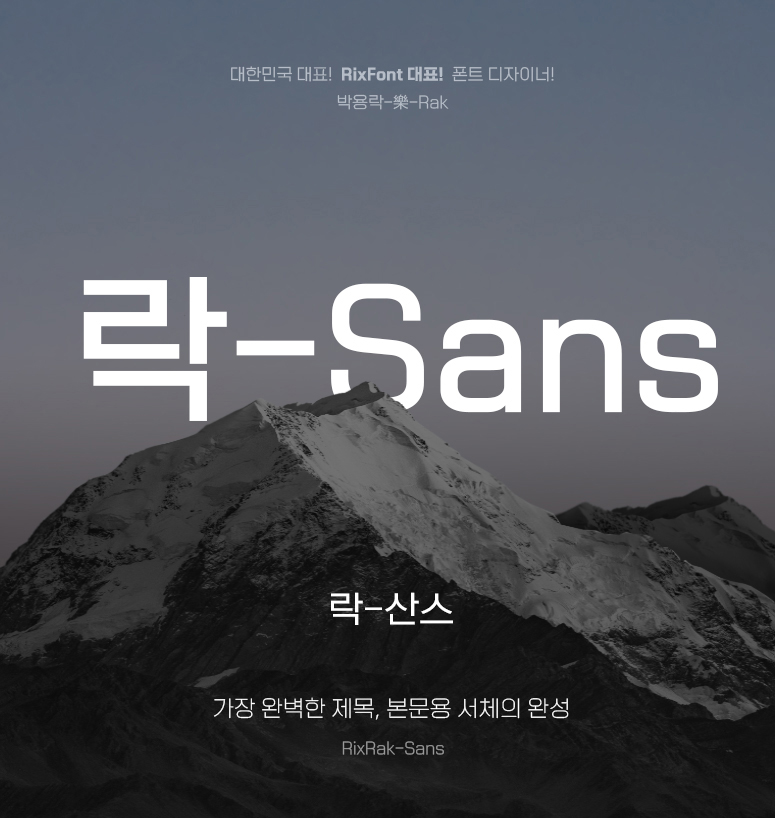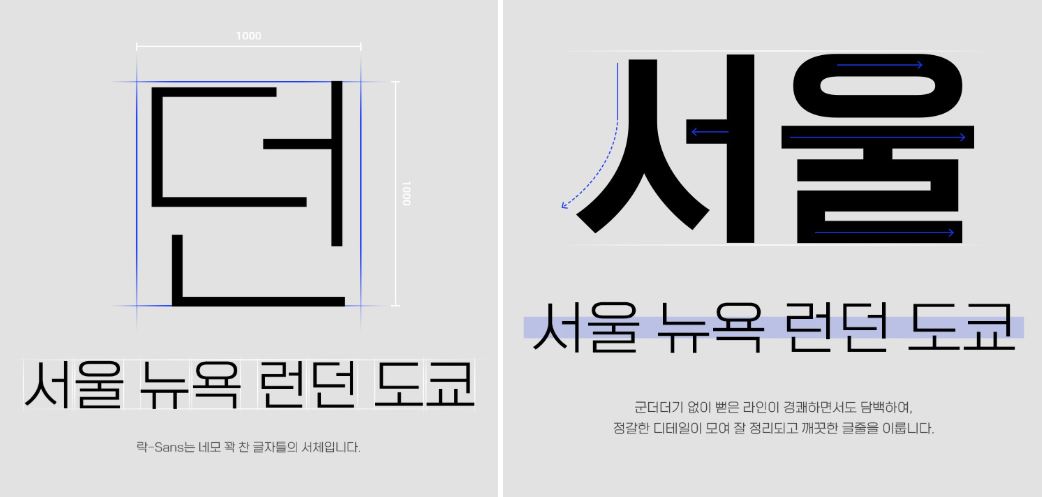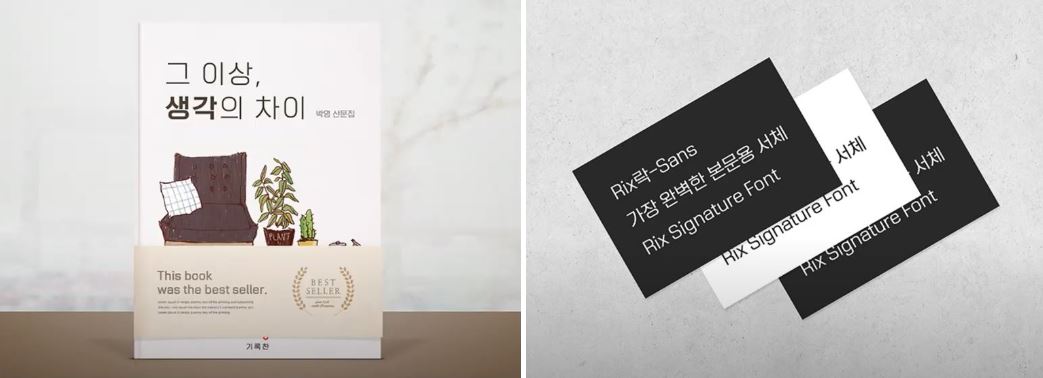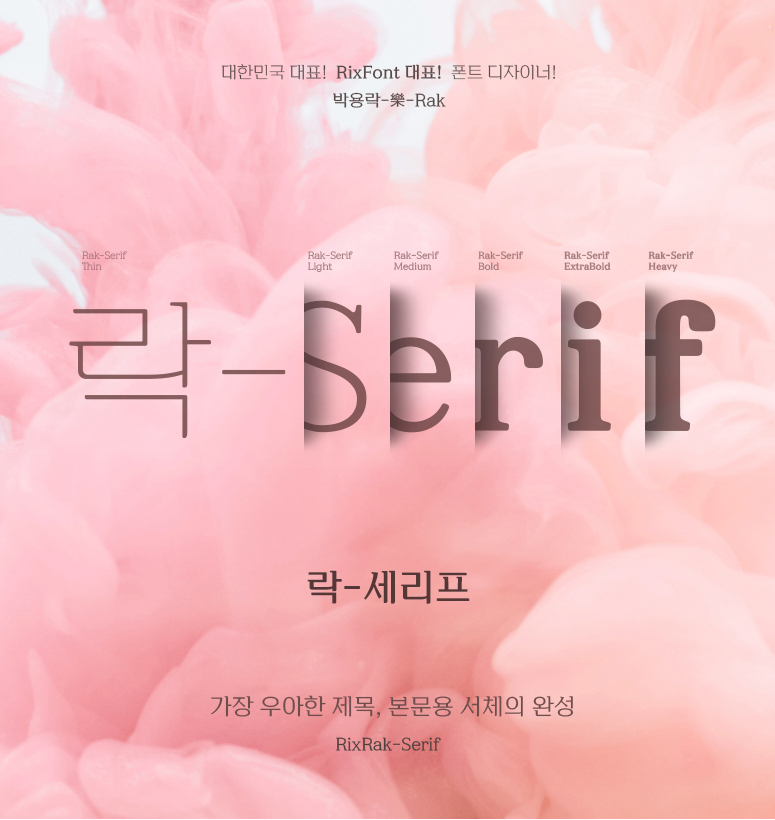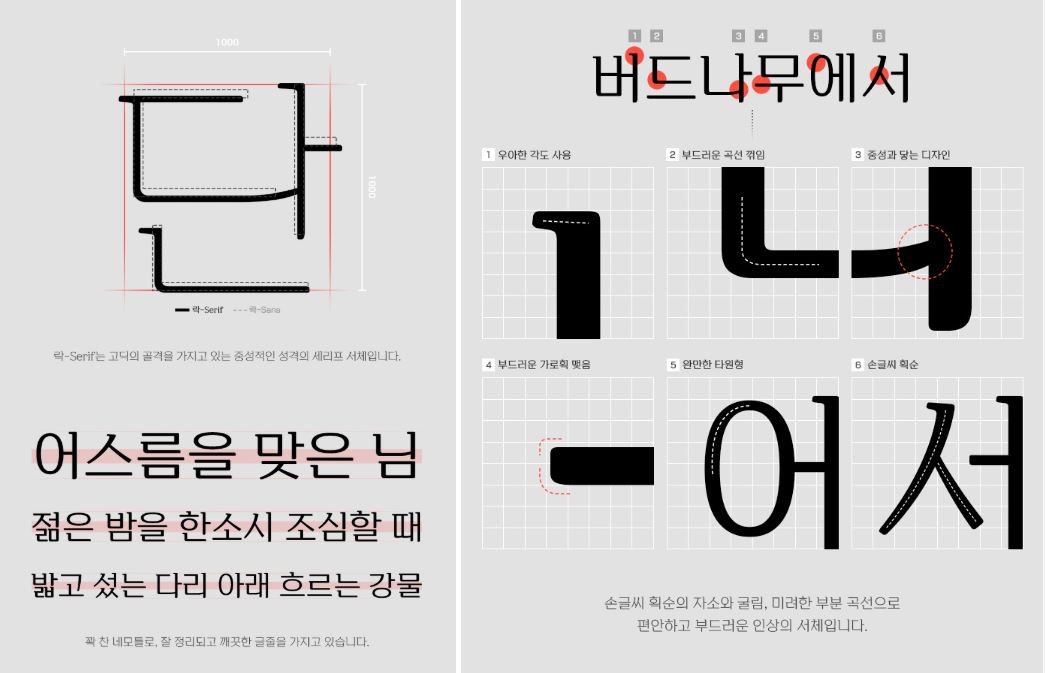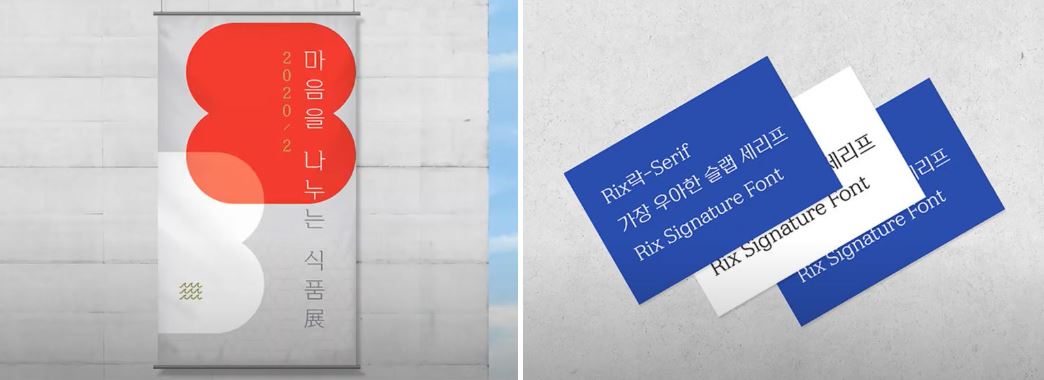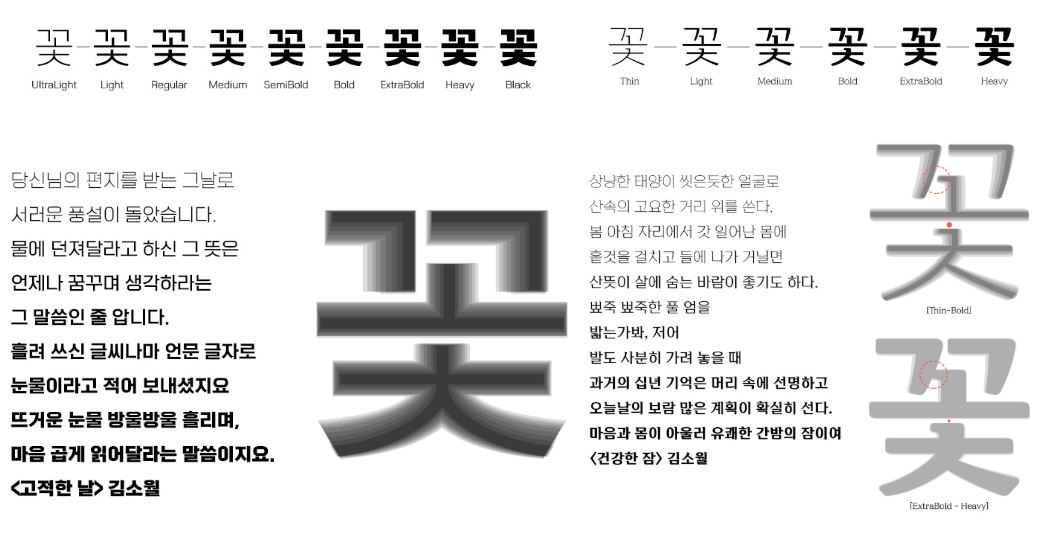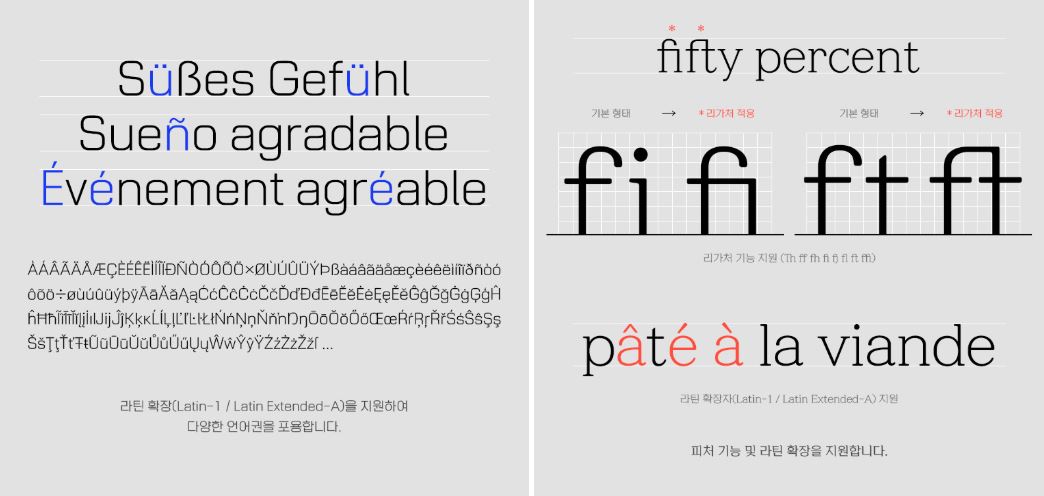
리뉴얼과 함께 RixFont의 시그니처가 될 신서체 2종을 소개해드립니다.
삼성의 전용 서체 '삼성원', 티몬의 '몬소리체', 네이버의 '나눔명조' 등 이미 독보적인 서체들을 많이 제작하신 대한민국 대표 폰트 디자이너, 박용락 디자이너님이 직접 디자인한 새로운 서체라 더욱 기대가 됩니다.
먼저 비하인드 스토리를 들어볼게요!
| Rix락-시리즈, 어떻게 시작하게 되었나요?
폰트 디자이너가 자기 이름을 폰트 이름에 건다는 건 쉽지 않은 결정입니다.
아직 폰트 디자이너로서 좀 더 수련해야 된다는 걸 알지만 폰트릭스의 브랜드 네임이 'Rixfont'로 바뀌고 홈페이지도 개편 됨에 따라 대표 상품이 필요하다는 마케팅 부서의 요청도 있고 이번이 끝이 아닌 시작이라는 생각으로 출시하게 되었습니다. 향후 업그레이드도 지속적으로 할 생각이며 Rix락-시리즈도 계속 만들어갈 생각입니다.
| 어떻게 기획하고 제작했나요?
Rix락-Sans, Serif 두 가지 스타일의 신서체를 만들었습니다. 모두 요즘 경향이라고 할 수 있는 꽉 찬 골격을 가지고 있어서 글줄이 잘 정리되게 보입니다. 그래서 단문장 위주의 영상 자막이나 UI 용도를 생각하며 제작하였습니다. Rix락-Sans, 와 Rix락-Serif 두 개의 서체를 기획할 때 우리가 주로 사용하는 고딕과 명조의 세트처럼 붙어 다니게 기획하였습니다. 그래서 같은 이름 뒤에 Sans, Serif 라고이름을 붙였지만, 엄밀히 얘기하면 Serif 서체는 명조는 아닙니다. 그래픽 서체에 좀 더 가깝다고 할 수 있습니다.
| 락-시리즈 폰트의 특징을 알고 싶어요.
Rix락-Sans는 앞서 꽉 찬 네모틀의 글자틀을 가지고 있다고 했는데, 태생적으로 레트로 느낌이 나게 되어 있습니다. 이를 최소화하기 위해 꾸밈 요소를 최대한 배제하여 잘 정리되고 깨끗한 모던한 도시의 느낌이 나도록 하여, 기존 시장에 나와 있는 네모틀 글자들과의 차이를 두었습니다. 공간구성의 높은 완성도도 차이라고 말씀드리고 싶습니다. 스펙은 총 9개의 두께로 구성되어 있으며 라틴 확장(Latin-1, Latin Extended-A) 뿐만 아니라 한자를 추가하여 사용성을 높였습니다.
Rix락-Serif는 Sans처럼 꽉 찬 골격 위에 Slab Serif를 접목하였고 이와 어울리게 부드러운 요소를 사용하여 Sans보다 중성적이지만 세련된 여성적 느낌이 나게 제작하였습니다. 스펙은 총 6개의 두께로 구성되어 있으며 영문에 리가처(Ligature) 기능과 라틴 확장(Latin-1, Latin Extended-A) 뿐만 아니라 한자를 추가하여 사용성을 높였습니다. (리가처 기능이란 두 개 이상의 글자가 만났을 때 하나의 글자로 다듬어져서 변하는 것을 의미합니다.)
| 앞으로의 기대와 방향성
경험상 감정을 최대한 자제한 건조하고 중립적인 글꼴들이 오랜 시간 사용해도 질리지 않고 많이 사용되는 것을 보아 왔습니다. 기존에 나와 있는 꽉 찬 골격의 서체와 완전히 다른 차별화된 서체라고 말씀드릴 수 없지만 향후 질리지 않고 오래 쓸 수 있는 이 분류의 대표 서체로 자리매김 되길 바라봅니다. 이제까지 저의 대표 서체는 나눔 명조나, 윤고딕시리즈, Rix고딕, 삼성원 서체였지만 향후 Rix락 시리즈가 대표 서체가 될 수 있도록 지속적으로 노력해 나가겠습니다.
모던함의 기준이 되는 Rix락-산스
가장 완벽한 제목과 본문용 서체, 「락-Sans」
보시다시피 깨끗한 스퀘어 구조로 모던하고 도시적인 느낌을 강조한 서체입니다.
타이틀용으로도 굉장히 돋보입니다.
네모틀에 꽉 차게 들어간 모습.
깔끔하게 뻗은 라인들이 잘 정리되어 보이고 단단한 느낌을 주어 가독성 또한 높습니다.
인쇄물에 들어가면 이렇게 현대적이고 깔끔한 인상을 줍니다.
책 제목용 폰트로도 적합하고, 세련된 느낌을 줄 수 있는 서체입니다.
중성적인 부드러움 그 자체 Rix락-세리프
가장 우아한 제목과 본문용 서체, 「락-Serif」
고딕의 남성적인 느낌과 여성적인 부드러운 선을 모두 갖고 있는 서체입니다.
두 가지 특징을 모두 담아내 편안하고 부드러운 인상을 줍니다.
명조체에서 보이는 글자 획의 일부 끝맺음이 돌출된 모양을 '세리프'라고 하는데요.
'락-세리프'는 그중에서도 끝이 굵은 사각 형태의 모습을 보이는 슬랩 세리프(Slab serif)의 특징을 갖고 있습니다.
인쇄물에 들어가면 이런 느낌을 줍니다.
정말 중성적이면서도 부드러운 인상을 주지 않나요?
이번엔 두 서체를 비교해볼게요. 왼쪽이 '락-산스', 그리고 오른쪽이 '락-세리프'입니다.
'락-산스' 서체는 총 9가지, '락-세리프'는 총 6가지 웨이트(굵기)로 구성되어 있습니다.
굵기 선택의 넓은 스펙트럼으로 활용도와 사용성을 높였습니다.
두 서체 모두 라틴 확장을 지원하여 다양한 언어권을 사용할 수 있습니다.
역시 영문도 '락-산스'는 깔끔하고 모던한 느낌. '락-세리프'는 클래식한, 고전적인 느낌을 주네요.
이렇게 '락-시리즈'의 두 가지 서체를 알아봤는데요.
앞으로 여러 방면으로 유용하게 쓰일 것 같은 느낌이 듭니다:)